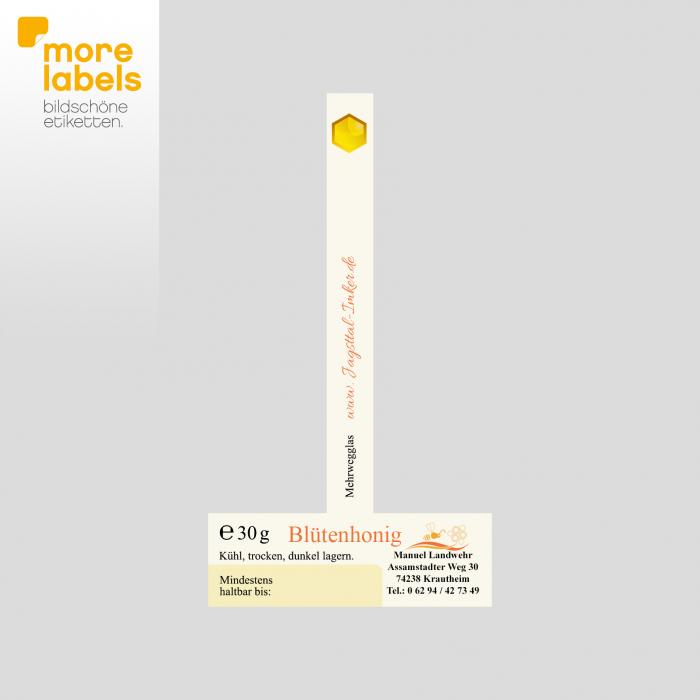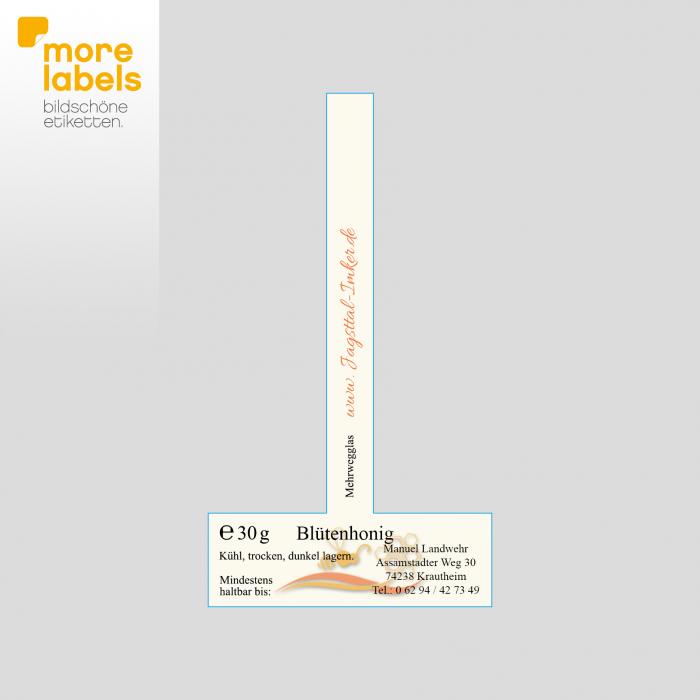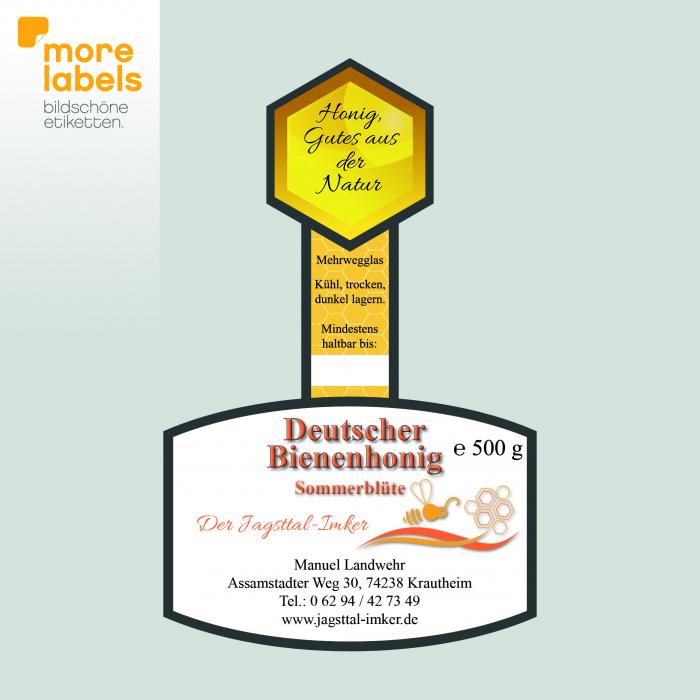
Für Honigetiketten passende Schrift
eins vorab, ich habe mit Schriften und Schriftarten recht wenig am Hut. Ich gestehe auch, ich möchte kein Profi werden was Schriften betrifft, da ich es meiner Meinung nach nur bei zwei-drei Sachen brauche welche mir extrem wichtig sind. Von daher hoffe und bitte ich euch um eure Hilfe.
Es geht um meine Honigetiketten die ich angefügt habe. Das Design finde ich ganz passabel und ansprechend, nur bin ich mit der Schrift noch nicht irgendwie zufrieden, bzw. weiß nicht ob ich da Fehler gemacht habe.
Benutzt habe ich Times New Roman als Standard Schrift und für die Schreibschrift benutzte ich Allura. Diese hatte ich gewählt da mein ursprüngliches Logo mit dieser Schrift versehen war, welche aber inzwischen entfernt wurde. Smit wäre Allura nicht mehr unbedingt von Nöten.
Da ich die Schriftarten durch alles hindurchziehen möchte (Etiketten, Webseite, Logo, Briefkopf (wer weiß ob ich das jemals brauche)) hoffe ich von euch ein Tipp zu bekommen welche Schrift ich am besten nutzen soll, oder ob ihr meine gewählten Schriften sogar schon als passend findet.
Eins noch zu meiner Person. Ich bin Jungimker im 2ten Jahr, ich habe mit meiner Imkerei bis jetzt keinen Cent verdient und werde die nächsten 2 Jahre wohl auch nicht viel einnehmen. Wenn ich irgendwann in der glücklichen Lage bin etwas mehr Geld abzweigen zu können, werde ich auch eine Agentur für sowas engagieren, aber bis dahin muss ich mit meinen wenigen bescheidenen Fähigkeiten auskommen und nehmen was dabei rauskommt.
Etikett 30g Glas
Etikett 500g Glas
Wenn sich hier noch niemand gemeldet hat, so hat das vermutlich nichts damit zu tun, dass man Dir nicht helfen möchte, sondern dass die hier versammelten Profis ob Deiner Vorlagen erst einmal durchschnaufen müssen. Vielleicht überlegt sich der eine oder die andere noch, wie man etwas dazu sagen soll, ohne Dir zu sehr auf den Schlips zu treten. Damit möchte ich möglichst taktvoll gesagt haben, dass ich es schwierig finde, aus Deinen Vorgaben etwas Gutes zu machen. Das ist bisher einfach nur ein Durcheinander von Gestaltungselementen ohne System. Aber nachdem Du ja selbst schreibst, dass Du »die Schriftarten durch alles hindurchziehen« möchtest, scheint mir da doch ein gewisses Bedürfnis nach konsistenter Gestaltung vorhanden zu sein. Vielleicht überlegst Du ja erst einmal selbst, an welchen Stellen Du konsequenter sein (Mittelachse) oder reduzieren könntest (Schriftarten und -größen, Einsatz von anderen Schriftattributen wie Farbe, Outline und Schatten), wo sich Elemente im Weg stehen (die Zeichnung hinter dem Text), was die Zeichnung überhaupt sein soll und ob sie in sich stimmig ist ...
ich denke, auf den Schlips bist du mir ganz sicher nicht getreten, im Gegenteil. Wenn ich nicht besser werden wollte, dürfte ich auch nicht nach Meinungen von Experten fragen. Solange die Antworten höflich sind, nehme ich jede Kritik an ;)
Mir ist bewusst das ich nicht Ansatzweise an Profis rankomme und es auch nie werde. Deswegen habe ich geschrieben, ich muss mit meinen bescheidenen Fähigkeiten das bestmöglichste rausholen und hoffe auf Unterstützung. ;)
Ich bin mir jetzt nur nicht ganz sicher, ob du von beiden Etiketten sprichst, oder speziell von dem 30g Glas. Dazu kann ich sagen, dass es eine überarbeitete Version gibt (unten angehängt), da es sogar mir aufgefallen ist, dass es nichts war ;)
Ich weiß nicht inwieweit ihr Einsicht in die Lebensmittelverordnung habt, aber es gibt da leider Verordnungen die eine gewisse Größe der Schrift zwingend vorschreibt, ebenso ist das kleine e vorgeschrieben das es mit einer Bestimmten Schriftart zu versehen ist…ich habe Arial genommen, da es meiner Meinung nach am nächsten ran kommt (Ich habe nirgends eine Definition der Schriftart gefunden :( ).
Dies versuchte ich durch das ganze Etikett zu ziehen (beim 500g Glas ist es mir mehr oder weniger gelungen, 2 Schriftarten, nur 2 verschieden Farben der Schrift).
Beim 30g Glas war es mir leider nicht ganz so leicht möglich. Aber, hier sind die Möglichkeiten noch mehr eingeschränkt. Ich kann außer dem Logo und der Internetadresse eigentlich nichts weglassen. Wie man da was vernünftig gestalten soll???
Beim 30g Glas habe ich nun auch alle Spielereien weggelassen was Texteffekte waren.es wirkte überhaupt nicht. Meint ihr es soll auch beim 500g Glas weg?
Ich bin froh über jede noch so kleine Hilfe die ich bekommen kann, ich bin kritikfähig und versuche auch nach meinen Möglichkeiten die Hilfe umzusetzen.
Manuel
Beim 30g Glas habe ich nun auch alle Spielereien weggelassen was Texteffekte waren.es wirkte überhaupt nicht. Meint ihr es soll auch beim 500g Glas weg?
Eindeutig ja. Das 30g Glas schaut so schon erheblich aufgeräumter aus.
Und dann bedenke, wenn nich hier, egal ob vom Marktstand oder beim Imker daheim mir ein Glas Honig kaufe, wär mir sogar egal, wenn es nur ein handgeschriebener Zettel wär, weil ich eben einen ehrlichen Honig aus der Region und nicht einen Verschnitt aus Importhonig von Sonstwo aus dem Supermarkt möchte. In so fern braucht es eigentlich keiner tollen "Marke". Hier spricht allein das Produkt, und die Tatsache, dessen Ursprung zu kennen.
Und so ist es dann eben auch besser, wenn man dies eben deutlich aus dem Etikett erkennen kann, gern in schlichtester Schrift.
Hier habe ich das mal an drei verschiedenen Schriften gezeigt. (Arial (ja ja, ich weiß ;-) ), Bernhard MT Condensed und Centaur)
Alle drei Schriften sind in gleicher Schriftgröße geschrieben, der Rahmen ist dabei die Schriftgröße.
Bei der Verpackungsgestaltung misst man diese Dinge deswegen in Millimetern aus – die Schriftgröße ist da keine verbindliche Einheit.  :nicken: